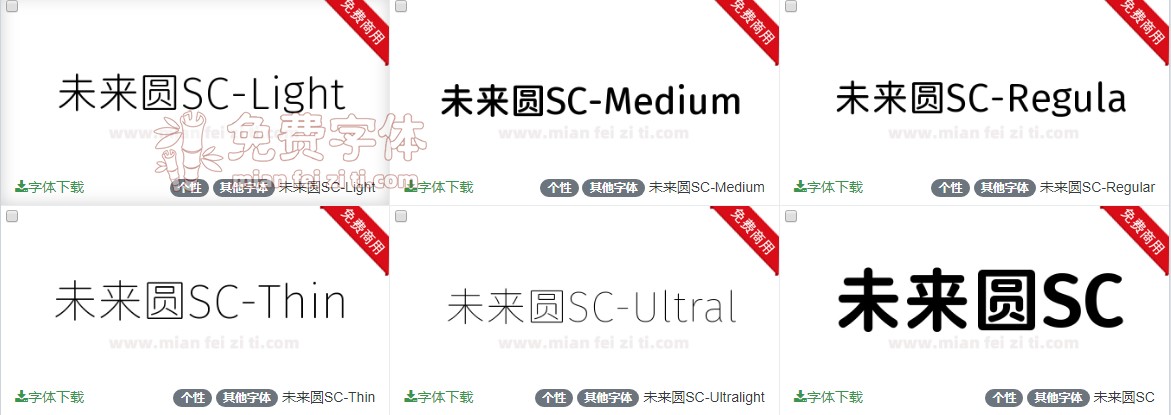
未来圆:皎皎白驹 其人如玉 基于未来荧黑改造更加简明现代圆体字体资讯
未来圆便是由未来荧黑所衍生的由博主独立制作而来的圆角化产物。相比于思源黑体,未来荧黑的造型更加简明现代,版面效果清新轻快。未来荧黑的中宫与字面更加收敛,重心在字重之间经过了重新配置;笔画细节上处理得更加干练,简洁而平直化。您可以下载样张来预览未来荧黑的设计。
未来荧黑的实现介于参数化与轮廓滤镜,使用了图像处理算法对字形建模。字体的制作并没有借助字体设计软件,而是用一个Web实现的可视化调参工具来确定字体参数。
制作此字的初衷就是因为前段时间比较火的狮尾圆/系列,很多拔脚之后的字显得十分突兀,比如“日口国出”等等此类单结构的字。原作者可能不在意,所以后来还衍生了各种狮尾系列,但是这个问题依旧存在。博主便用了同宗同源的思源拔脚,制作了此版本(未来系列还有一个更优的地方,就是把原本的笔画不匀的地方,做了做大程度的优化。)因为算法不同,所以并没有狮尾系列这个毛病,理论及观感还有契合度,都是要优于狮尾系列的。起码这个十分突兀的问题,并不存在。顺道优化了字面尺寸,调取了book字重为常规字重。移植已经精修了其余字重,生成6字重版本的未来圆。开源衍生必定也是开源,但不可用作出售盈利使用,须知。